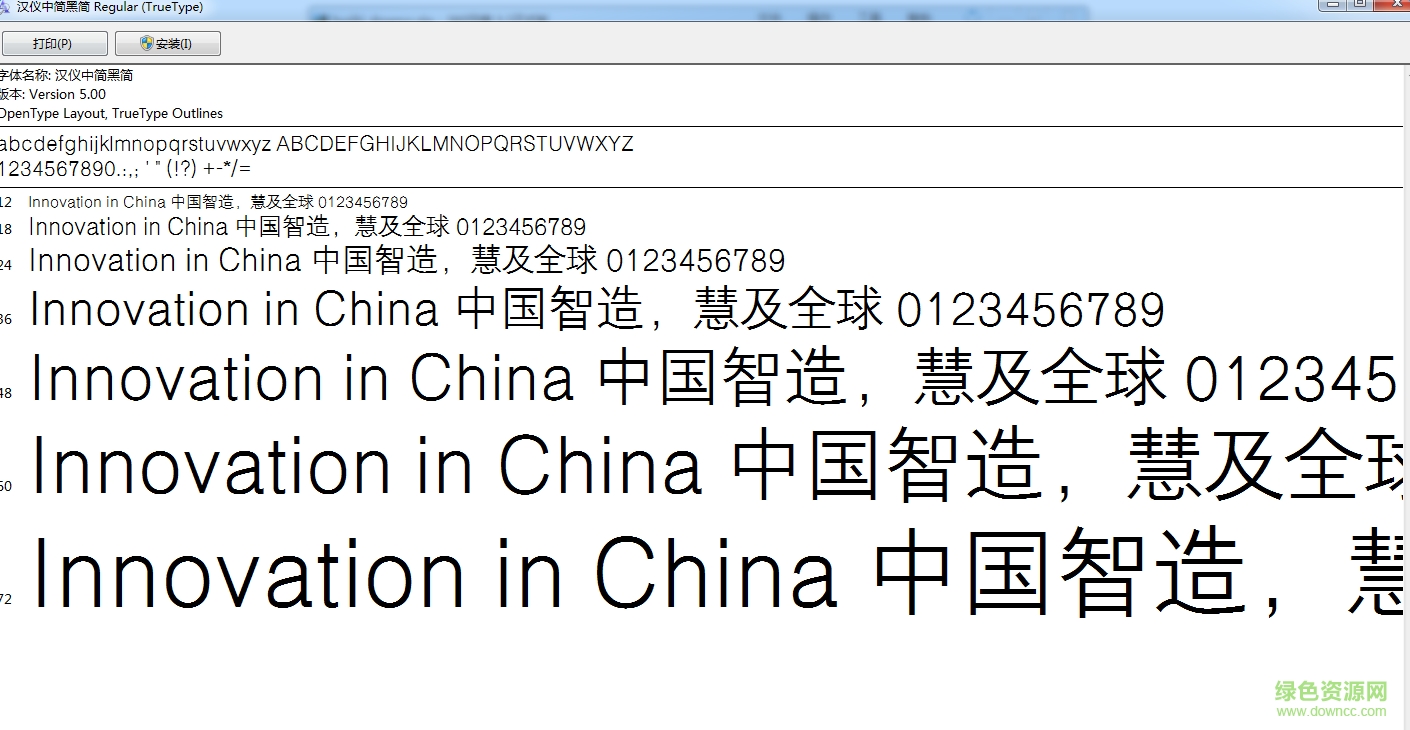
hyzhongjianheij
hyzhongjianheij字體又叫漢儀中簡(jiǎn)黑,是一款比較細(xì)的黑體字體,結(jié)構(gòu)精妙,筆觸纖細(xì),包裝設(shè)計(jì)、廣告設(shè)計(jì)、裝飾裝幀、印刷排版等領(lǐng)域都可以使用!
黑體介紹
黑體可細(xì)分為:粗黑、超粗黑(特黑)、大黑、細(xì)黑、美黑、宋黑、水黑、藝黑、氈筆黑、平黑等類型。